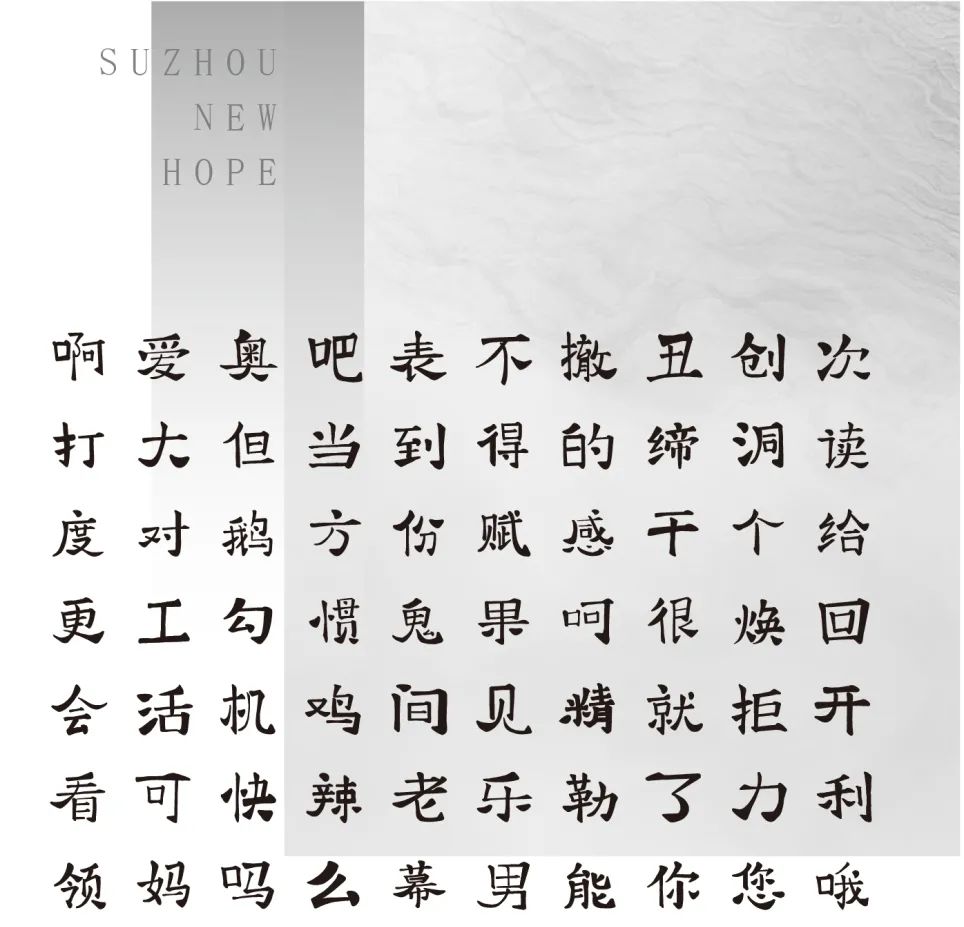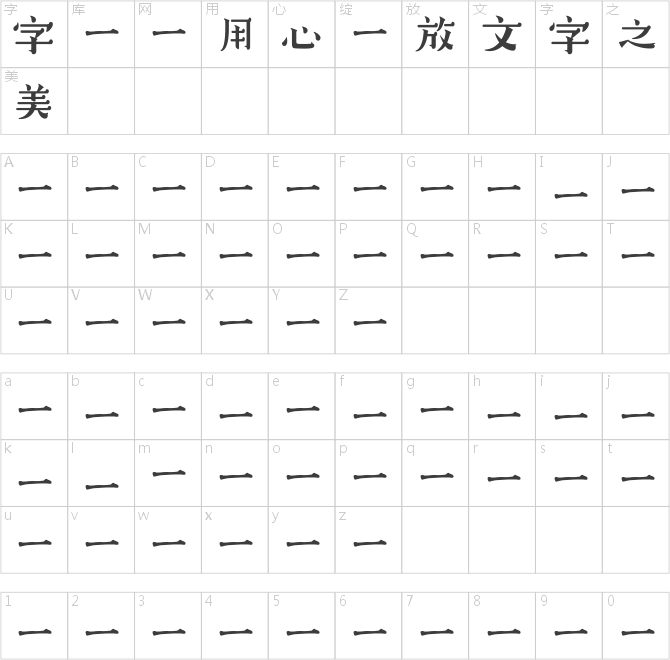
蘇州精致體
蘇州精致體介紹
蘇州新希望地產(chǎn)循跡蘇州的精致脈絡(luò),聯(lián)合“未來(lái)一代天才藝術(shù)家”、“90后新生藝術(shù)代表人物”——瞿子竣設(shè)計(jì)師,精心設(shè)計(jì)了一款獨(dú)屬于蘇州的字體——蘇州精致體,一撇一捺立于天地之間,一勾一畫(huà)書(shū)寫(xiě)蘇州文明。
“蘇州精致體”呈開(kāi)放式的筆畫(huà)布置,橫筆筆端作圓弧形翹起,撇點(diǎn)靈動(dòng)秀氣、字形優(yōu)美圓潤(rùn),整體借鑒了宋體印刷字體又不拘于常規(guī),展現(xiàn)隨性現(xiàn)代的美感。
在追隨經(jīng)典的同時(shí)尋找精致的格調(diào),通過(guò)比劃間微妙破筆、加減粗細(xì),拙筆來(lái)體現(xiàn)精致生活下的四味生活,再將蘇州人對(duì)追求的精致融為一體,創(chuàng)新嶄新時(shí)代精致的內(nèi)涵。
好的字體設(shè)計(jì)從來(lái)不囿于字體設(shè)計(jì),而是與文化底蘊(yùn)、情感內(nèi)涵一脈相承。
“蘇州精致體”是蘇州新希望地產(chǎn)與瞿子竣設(shè)計(jì)師一同開(kāi)啟蘇州精致文化想象力的鑰匙,它是蘇州語(yǔ)言在文化領(lǐng)域的一次重要實(shí)踐,以更為詩(shī)意的方式去傳遞蘇州的藝術(shù)文化,而在“蘇州精致體”這一文化符號(hào)的背后,亦是蘇州新希望地產(chǎn)對(duì)蘇州精致理念的無(wú)盡探索。